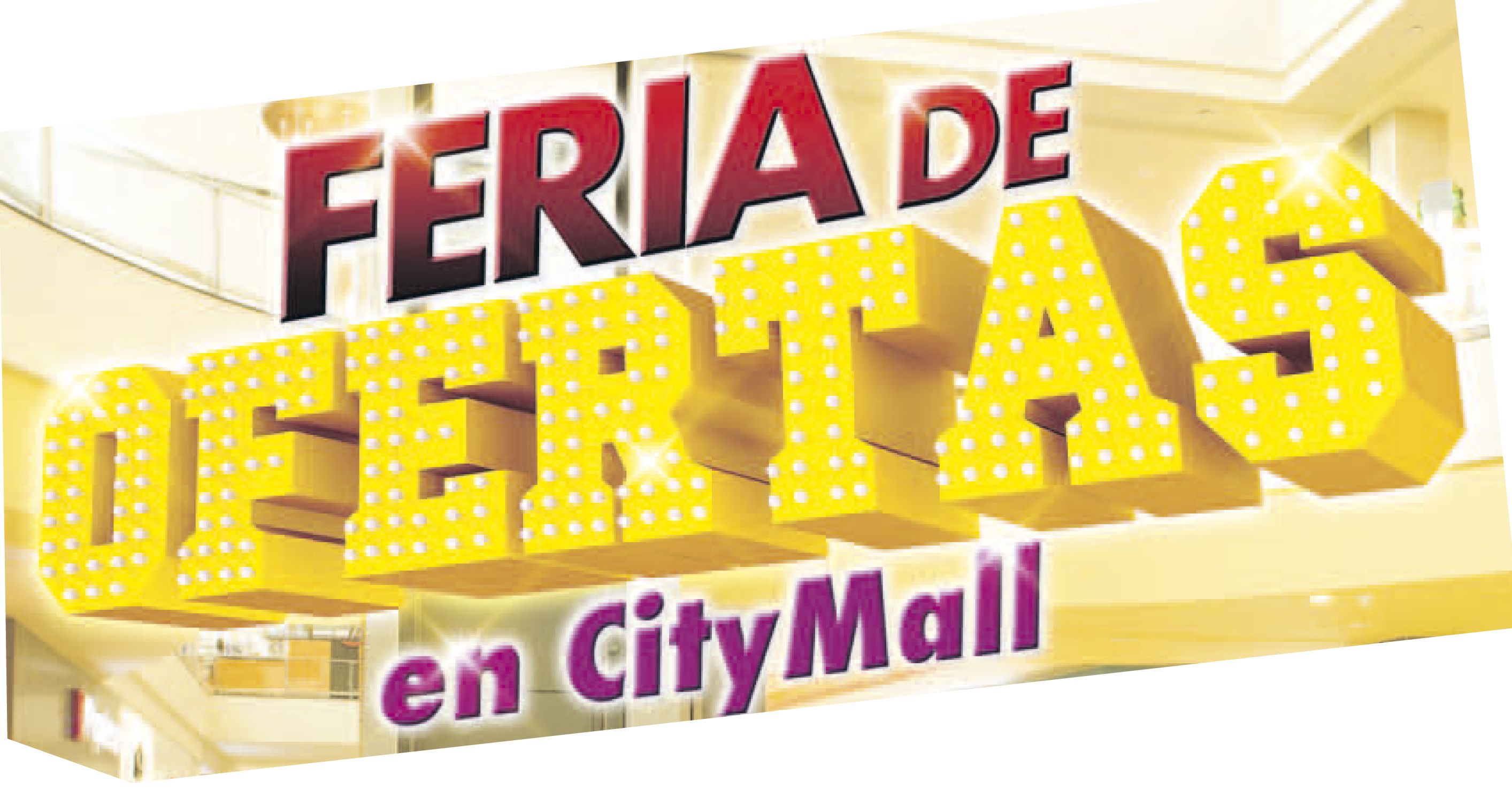
Foro de Tipografía Ayuda con efecto texto 3D el 16.10.2015 a las 01:18 por oraculoc4d · 1 comentario Seguir este tema Dejar de seguir este tema 1 seguidor Ayuda,... quisiera saber como y con que programa hicieron la palabra oferta, esas sombras y esos detalles quiero estudiarlos para manejar modelos similares. Gracias Comentar Me gusta